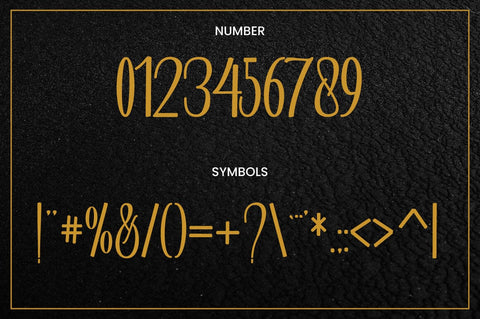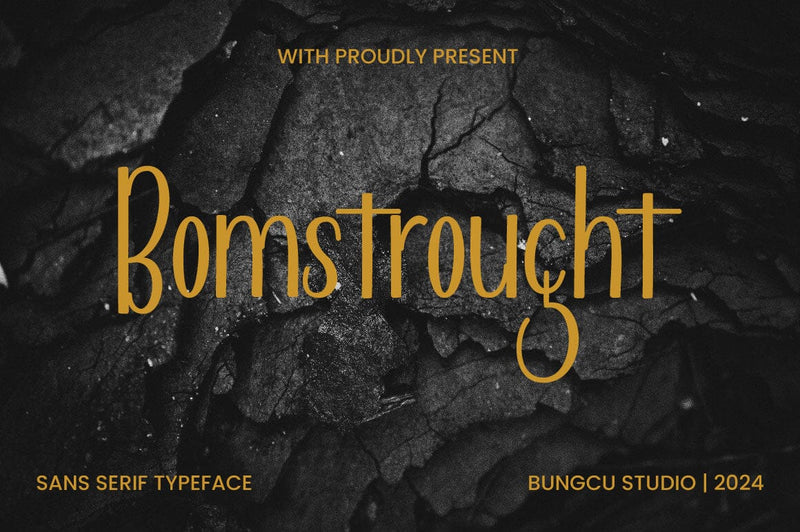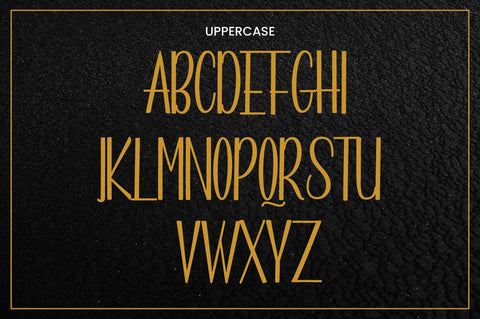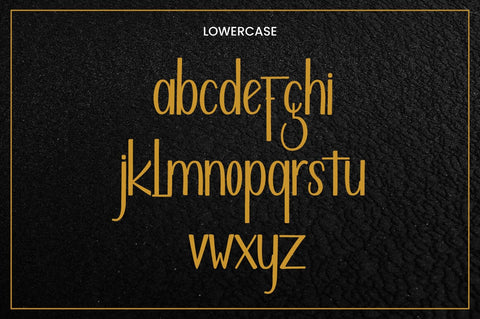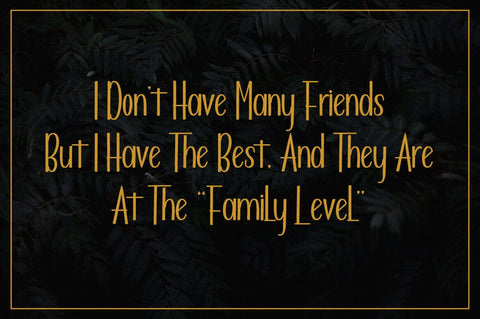
Bomstrought Font
Lahir dari kecintaan yang mendalam terhadap seni tulisan tangan, Bomstrought Font adalah pilihan sempurna bagi mereka yang mencari kesan berani, bersih, dan menyenangkan. Dibuat dengan cermat, font ini tidak hanya mempercantik kartu ucapan tetapi juga berfungsi sebagai pilihan ideal untuk dekorasi mug yang unik. Selain itu, Bomstrought Font terintegrasi dengan mulus ke dalam berbagai proyek tulisan tangan, memberikan sentuhan tak terlupakan pada setiap karya Anda.